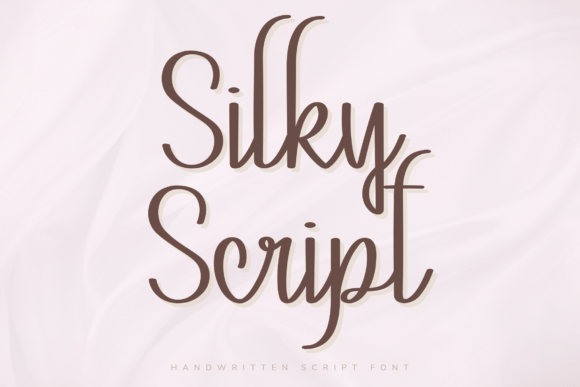
Silky Script
適切なデザイン要素を見つけるのは難しい場合がありますが、Silky Scriptは作品を即座に引き立てる優れたコレクションを提供します。
POD(オンデマンド印刷)製品、結婚式の招待状、またはソーシャルメディアのグラフィックを作成している場合でも、Silky Scriptは理想的です。